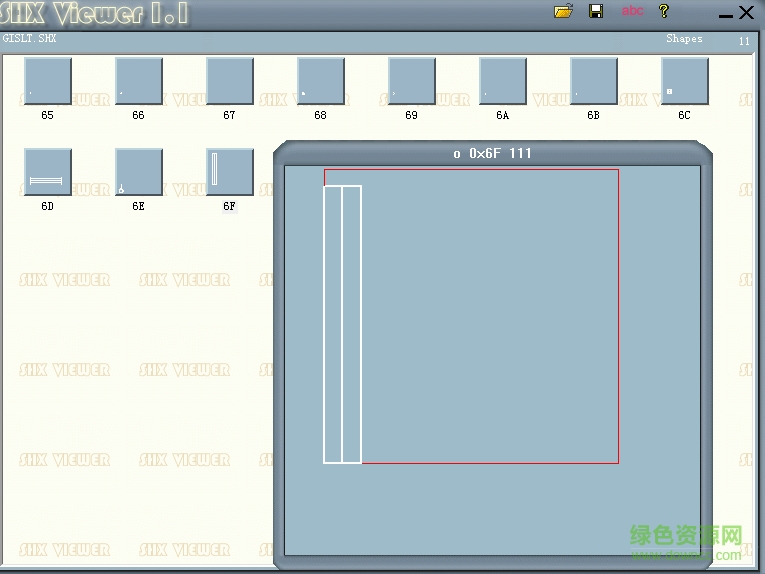
gislt.shx字體是一款體積非常小的cad字體,該字體線條分明,筆畫較硬,包含了各種小符號(hào),在電腦上顯示非常清晰,適合繪圖設(shè)計(jì),需要這款字體的朋友趕緊來綠色資源網(wǎng)下載吧!
autocad有自己的字庫(kù),在fonts目錄里。字體文件以shx為擴(kuò)展名,稱為shx字體。最初的shx字體支持的是ANSI字符,后來擴(kuò)大到支持非ANSI字符,也就是大字體或bigfont,用雙字節(jié)儲(chǔ)存,這也就是為什么叫大字體的原因。
微機(jī)系統(tǒng)的字體font。這類字體是電腦必用字體,存在于“fonts”文件夾里。
CAD字體主要是為CAD軟件提供顯示輔助,跟普通字體實(shí)際是一樣的意思。